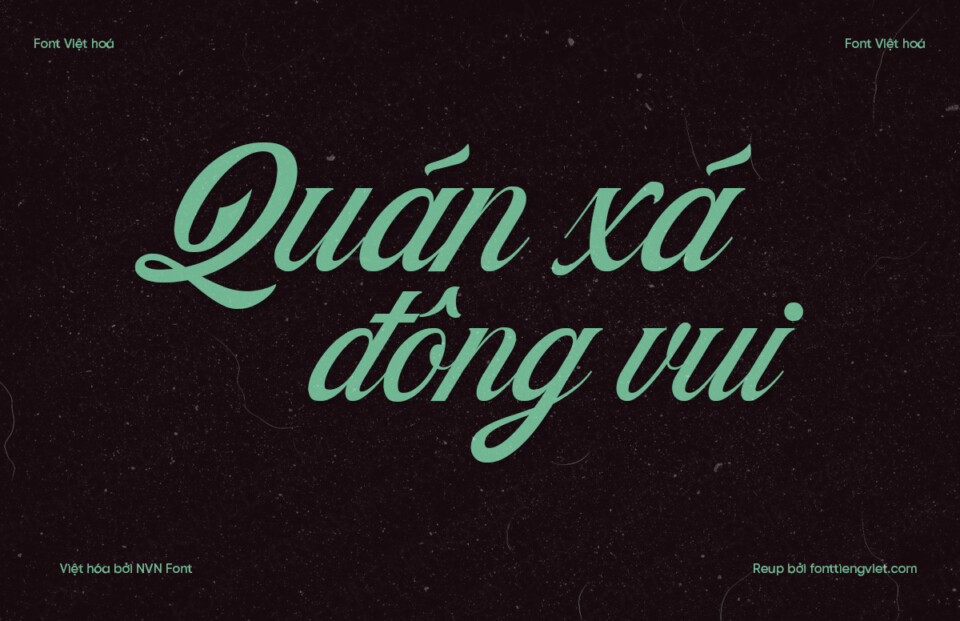
Font Việt hóa NVN Kingdrops
Font Việt hóa NVN Kingdrops – Sự kết hợp hoàn mỹ giữa nét cổ điển và hiện đại
Giới thiệu về Font Việt hóa NVN Kingdrops
Trong thế giới thiết kế đồ họa ngày nay, việc lựa chọn một bộ Font Miễn Phí chất lượng luôn là ưu tiên hàng đầu của các nhà sáng tạo. Một trong những cái tên nổi bật đang làm mưa làm gió trong cộng đồng thiết kế chính là Font Việt hóa NVN Kingdrops. Đây là một bộ font mang phong cách retro đầy cá tính, được tinh chỉnh tỉ mỉ để phù hợp với bảng mã tiếng Việt, giúp người dùng dễ dàng truyền tải thông điệp một cách ấn tượng nhất. Font Việt hóa NVN Kingdrops không chỉ đơn thuần là các ký tự, mà còn là một tác phẩm nghệ thuật giúp nâng tầm giá trị hình ảnh cho mọi dự án từ học đường đến chuyên nghiệp.
Đặc điểm nổi bật của bộ font NVN Kingdrops
Thiết kế độc đáo và linh hoạt
Font Việt hóa NVN Kingdrops sở hữu những đường nét mạnh mẽ, dứt khoát nhưng không kém phần mềm mại ở các góc bo tròn. Điều này tạo nên một cảm giác thân thiện, phù hợp với phong cách vintage của những thập niên trước. Bộ font này bao gồm nhiều biến thể khác nhau, từ nét thanh mảnh đến nét đậm, cho phép bạn tùy biến linh hoạt trong việc trình bày văn bản hoặc thiết kế tiêu đề. Đặc biệt, các dấu câu tiếng Việt được thiết kế cân đối, không làm phá vỡ cấu trúc tổng thể của chữ cái, giúp văn bản trở nên chuyên nghiệp và dễ đọc hơn bao giờ hết.
Ứng dụng đa dạng trong thực tế
Với vẻ ngoài bắt mắt, Font Việt hóa NVN Kingdrops thường được sử dụng rộng rãi trong thiết kế logo, bao bì sản phẩm, poster sự kiện và đặc biệt là các bìa sách dành cho học sinh, sinh viên. Trong môi trường học đường, giáo viên có thể dùng font chữ này để làm slide bài giảng thêm sinh động, kích thích sự hứng thú của học sinh. Đối với các bạn trẻ yêu thích sáng tạo nội dung trên mạng xã hội, bộ font này sẽ là công cụ đắc lực để tạo ra những hình ảnh trích dẫn (quote) triệu view mang đậm dấu ấn cá nhân.
Cách sử dụng Font Việt hóa NVN Kingdrops hiệu quả
Lưu ý khi phối hợp màu sắc
Để Font Việt hóa NVN Kingdrops thực sự nổi bật, bạn nên kết hợp với những tông màu trầm như nâu đất, vàng mỡ gà hoặc xanh rêu. Những gam màu này sẽ làm tôn lên vẻ hoài cổ của font chữ. Tuy nhiên, nếu bạn muốn một phong cách hiện đại hơn, việc sử dụng các cặp màu tương phản cao như đen – trắng hoặc đỏ – trắng cũng là một lựa chọn tuyệt vời. Hãy nhớ giữ khoảng cách giữa các chữ cái (kerning) ở mức vừa phải để đảm bảo tính thẩm mỹ cao nhất cho bản thiết kế của mình.
Lời kết về bộ font chữ ấn tượng